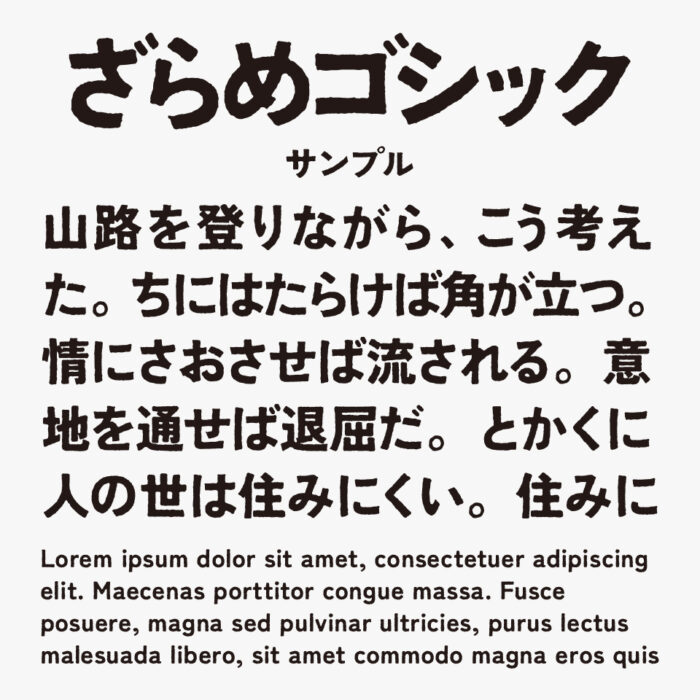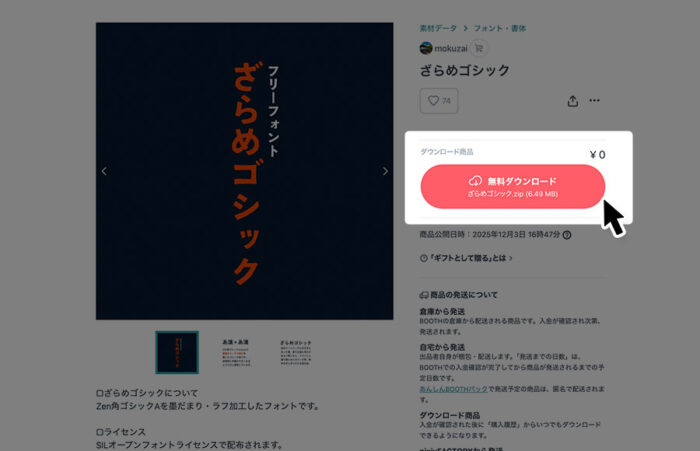
ざらめゴシック
ざらめゴシックは、Zen角ゴシックAntiqueをベースにして、墨だまり・ラフ加工したゴシック体フォントです。
筆で描いたようなざらつきのある線が特徴の文字にわずかなインクのようなにじみがあることで、デジタルすぎない、アナログ感のあるフォントとなっています。
和風デザインや、伝統×モダンを掛け合わせた表現にもぴったりで、墨だまり・ラフ加工が少しクセのある力強い存在感が魅力のフォントです。